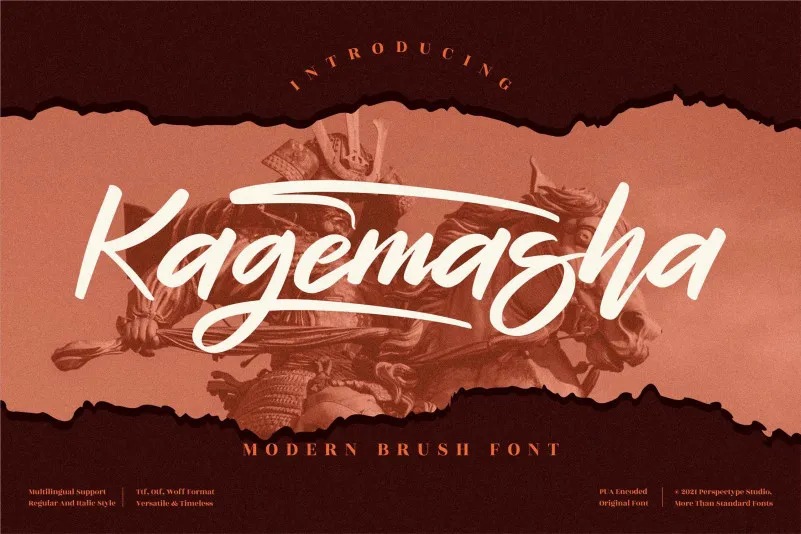
Esta é uma fonte script elegante inspirada no bela calligrafia clássica, mas com um tom contemporâneo e moderno. Seu estilo perfeitamente equilibrado e variado, foi projetado para destacar a beleza de seus projetos. Perspectype criou essa fonte para ajudar os designers a dar vida aos textos de maneira sofisticada e estilizada, oferecendo uma opção versátil que se encaixa perfeitamente em diversos estilos. Seja para cartazes, artigos de revistas ou até mesmo pequenos detalhes gráficos, Kagemasha Font traz profundidade e estilo à qualquer projeto.